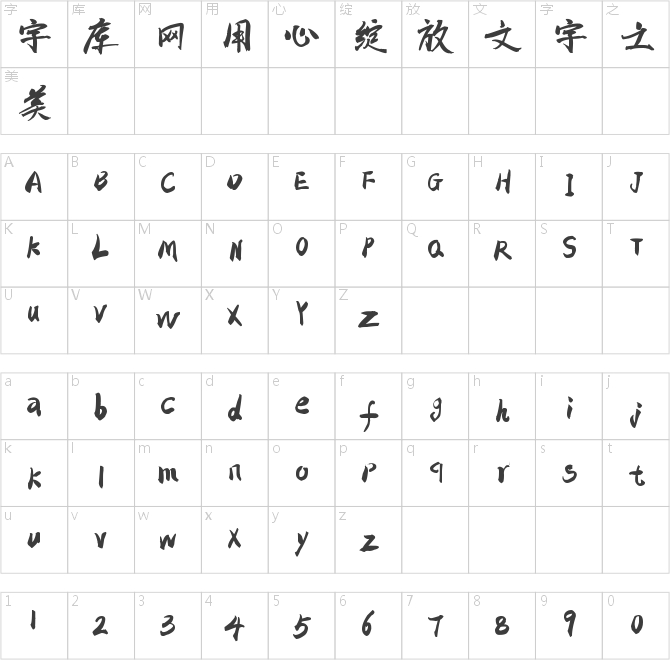
漢呈大黑手寫體 詳情頁
字體名稱: 漢呈大黑手寫體
漢呈大黑手寫體
漢呈大黑手寫體介紹
漢呈大黑手寫體字體字庫是一款讓人賞心悅目、百看不厭的中文字體,適合各類廣告和產(chǎn)品包裝設(shè)計應(yīng)用,字體大小4.13MB,格式為ttf字體,上傳用戶是漢呈字庫,作者/版權(quán)方為漢呈字庫